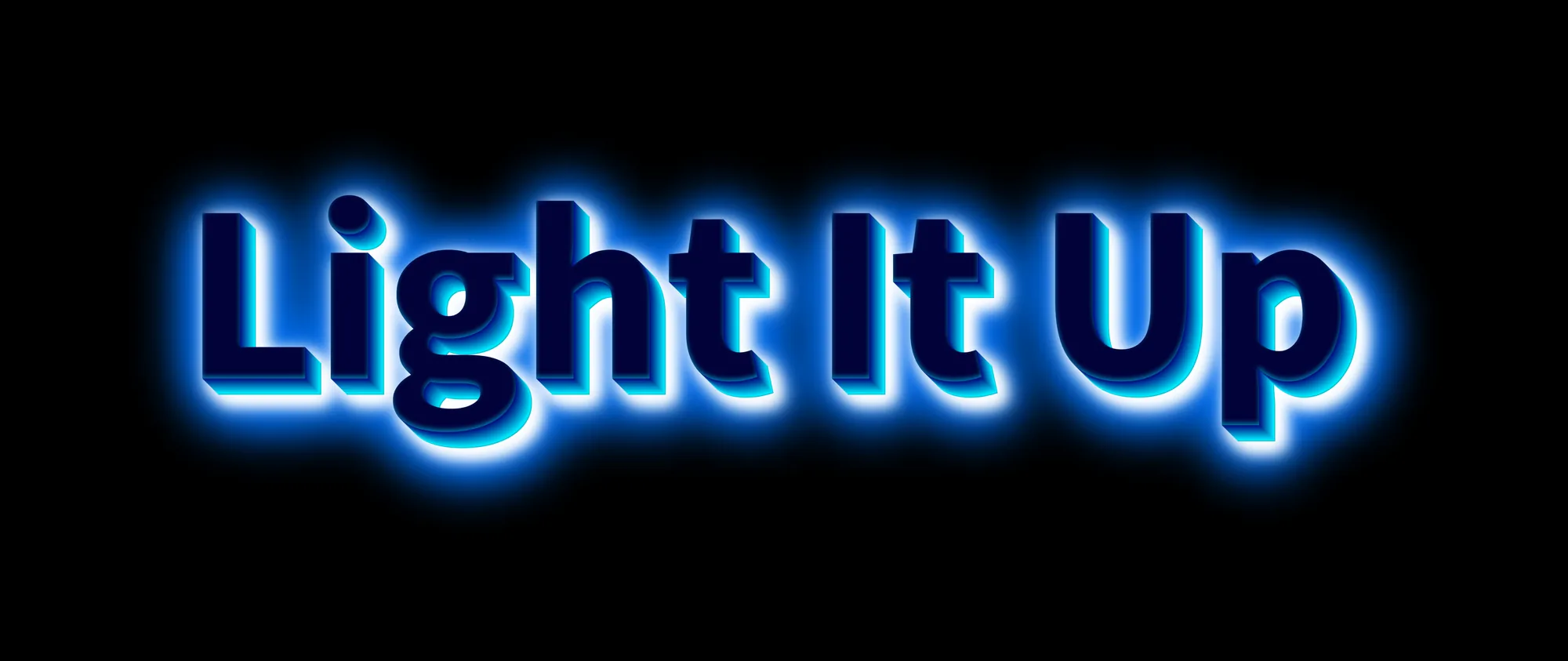
ネオンライトはいつだって視線を集めます。輝き、光を放ち、どんなシーンにも一瞬でエネルギーを与えてくれます。グラフィックデザインでも、ネオンフォントは同じ効果を発揮します。テキストを画面から浮かび上がらせ、生き生きとした印象に変えてくれるのです。ここでは、デザインを輝かせる鮮やかでカラフルなネオンテキストエフェクトの作り方を見ていきましょう。
ネオンフォントが特別な理由
ネオンフォントのスタイルは、本物のネオン管が放つ光の質感を再現します。明るい光で満たされた細く曲線的な文字は、クールなナイトライフの雰囲気をデザインに与えます。ピンク、ブルー、パープルといったネオンカラーが特に人気で、コントラストを最大限に引き出すダークな背景と組み合わせると最も映えます。
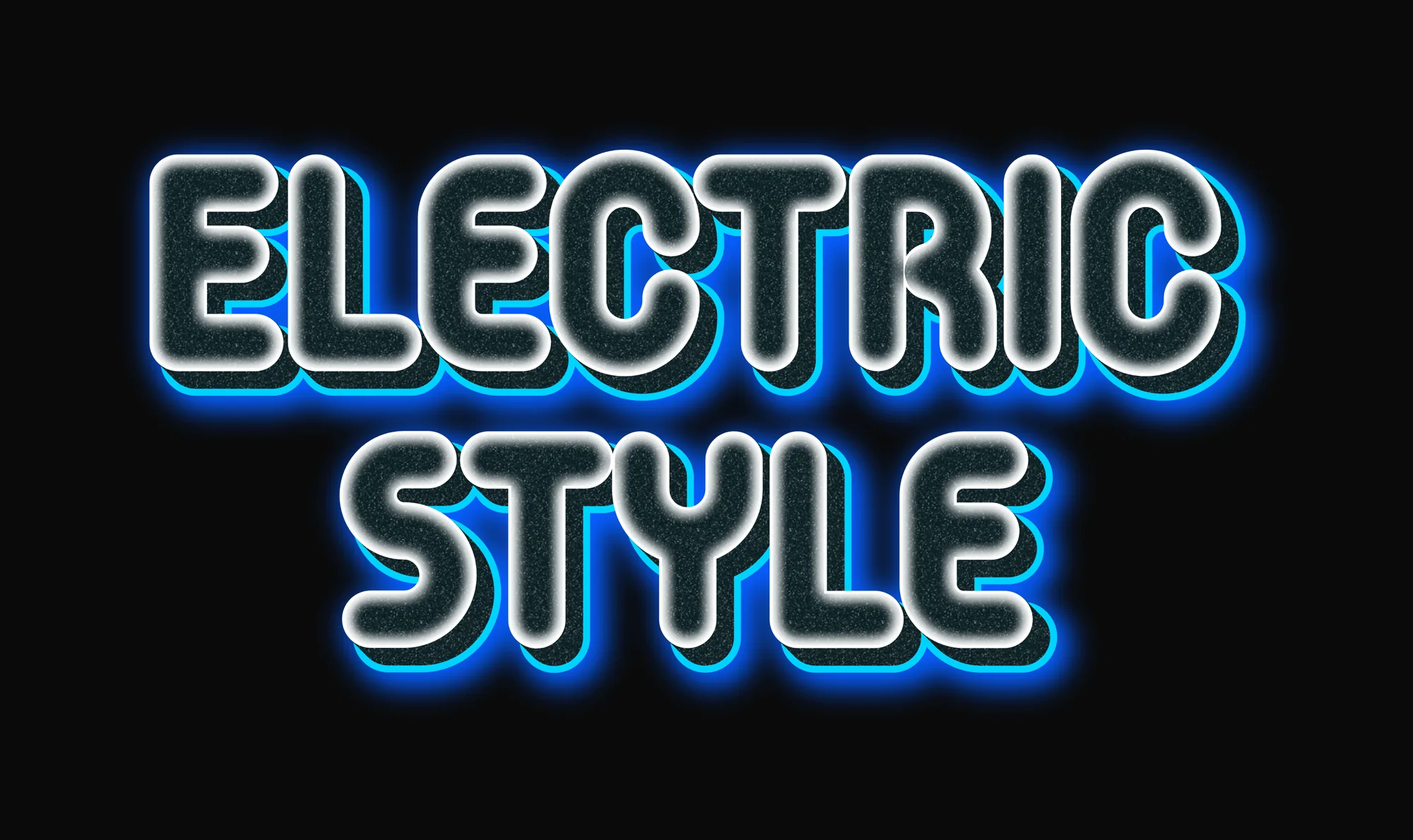
色と光で遊ぶ
ネオンテキストエフェクトの魅力のひとつは、カスタマイズがとても簡単なことです。発光にさまざまな色を混ぜたり、柔らかな影を加えて文字を際立たせたりしてみましょう。ピンクからブルーへのグラデーションや、ほのかな白い輝きは、モダンで幻想的な雰囲気を演出します。ポスターやSNSの投稿、デジタル招待状にぴったりです。それぞれの光るネオンテキストエフェクトを自分の言葉でプレビューすれば、色と光がどう見えるかを正確に確認できます。
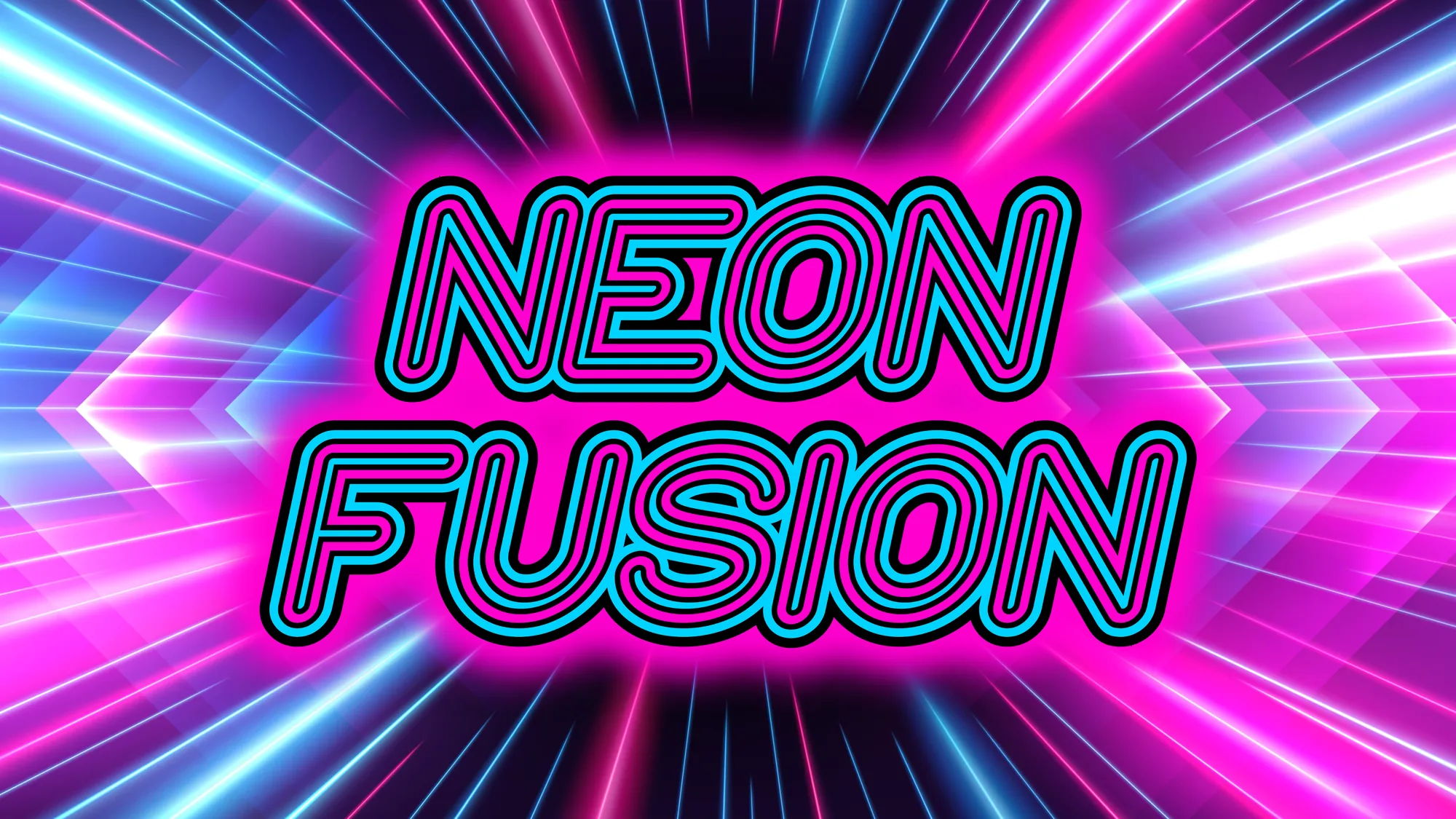
ネオンサインとレトロなインスピレーション
デザインの世界でネオンサインフォントが愛されているのは、ヴィンテージなカフェや街並み、レトロなクラブの看板を思い起こさせてくれるからです。この懐かしさのあるスタイルは、個性ときらめきを求めるロゴやYouTubeのサムネイル、イベント用のグラフィックにぴったりです。反射やぼかした光を組み合わせれば、よりリアルに仕上がります。
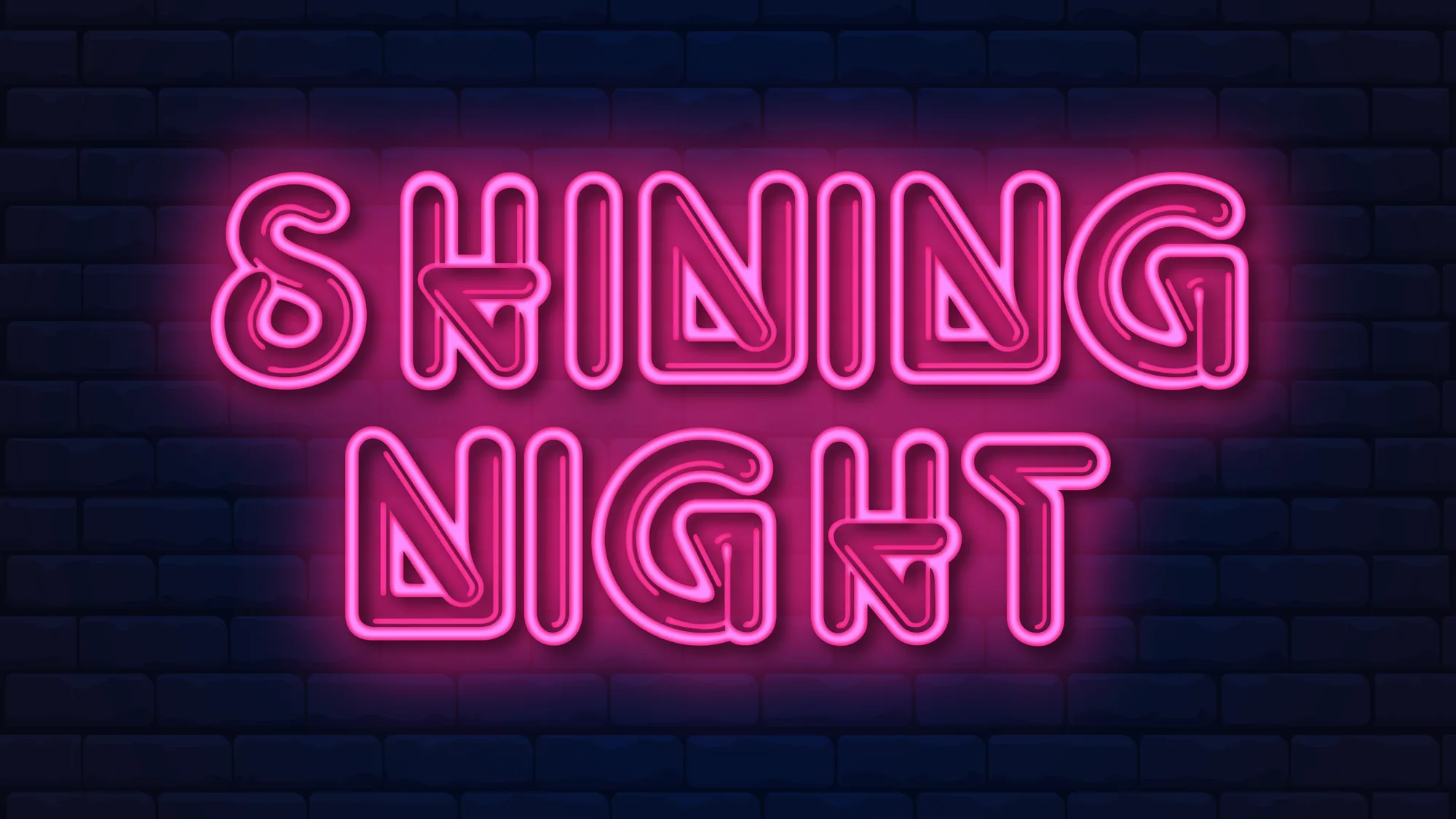
モダンなネオンタイポグラフィ
今日のデザイナーは、レトロな表現だけにとどまらず、創造的な新しい方法でネオンフォントを活用しています。太い文字とやわらかなグラデーションを組み合わせたグローフォントは、未来的でスタイリッシュな印象を与えます。オンラインのネオンテキストジェネレーターを使えば、自分の言葉を入力するだけで、瞬時に文字が光り出す様子を確認できます。すっきりとした背景と鮮やかなカラーパレットと合わせれば、音楽ジャケットやゲームデザインで見られるデジタルネオンの雰囲気が生まれます。
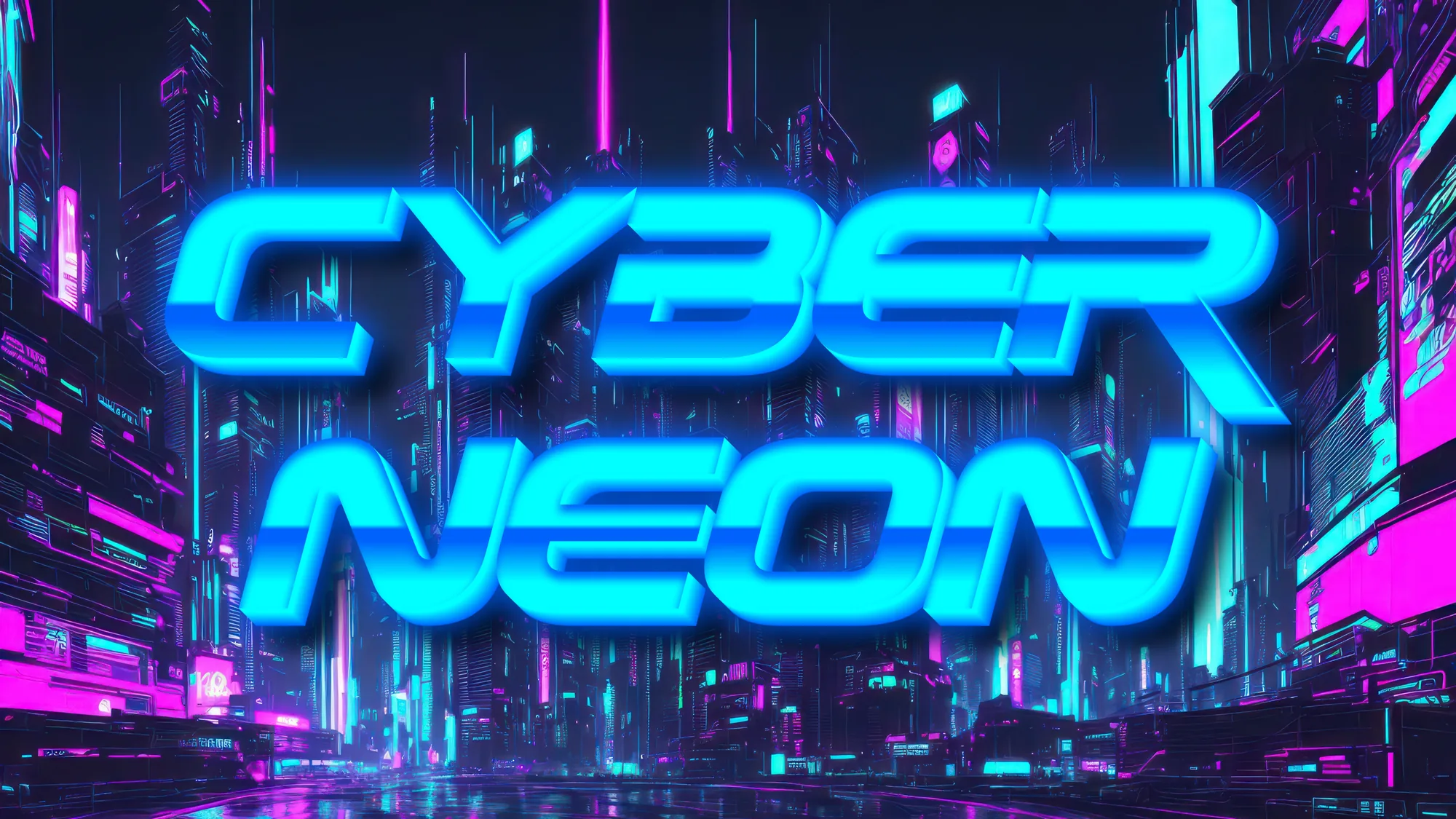
まとめ
ネオンフォントと発光エフェクトは、テキストに光を吹き込む楽しくクリエイティブな手法です。レトロからモダンまで、あらゆるメッセージに色とエネルギー、スタイルを添えてくれます。テキストが本当に輝き出すまで、さまざまな色合いや光、背景を試してみましょう。TextStudioのネオンテキストエフェクトのコレクションを使って、今日からあなただけの光るデザインを作り始めましょう。